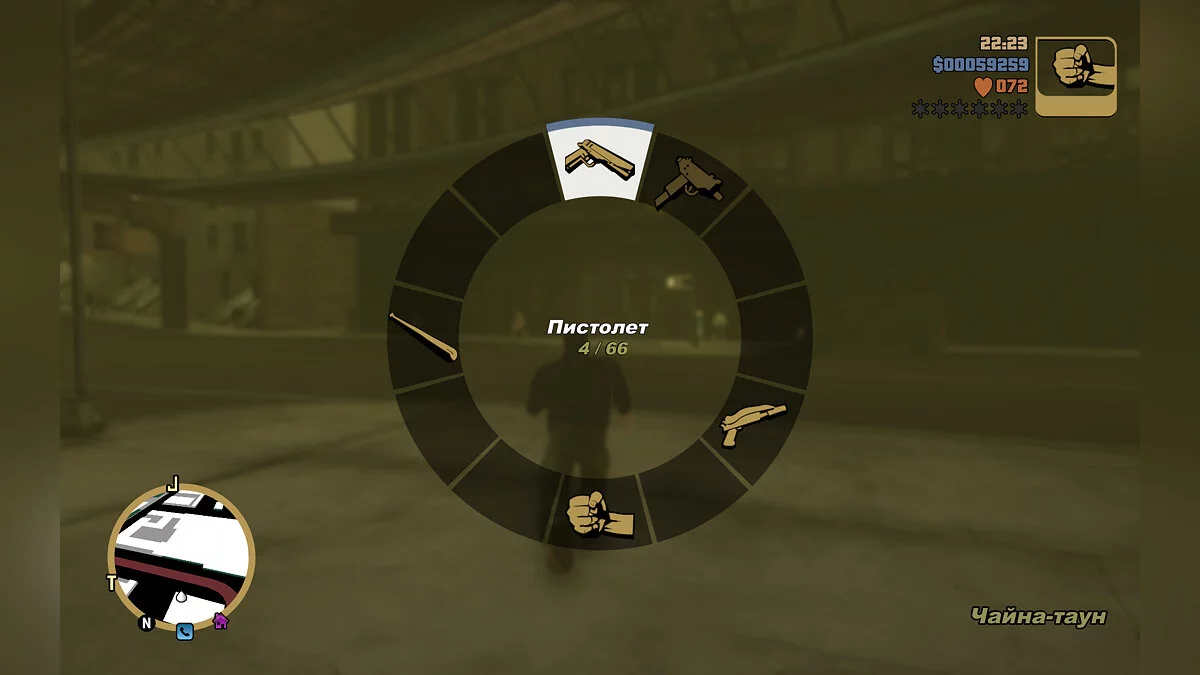
Оригинальный шрифт
Этот мод возвращает на место оригинальный шрифт из GTA3 в Definitive Edition. Оригинальный шрифт Arial Black по умолчанию не имеет курсивного начертания, поэтому его пришлось дорабатывать, чтобы он выглядел точно так же, как в оригинальной версии.